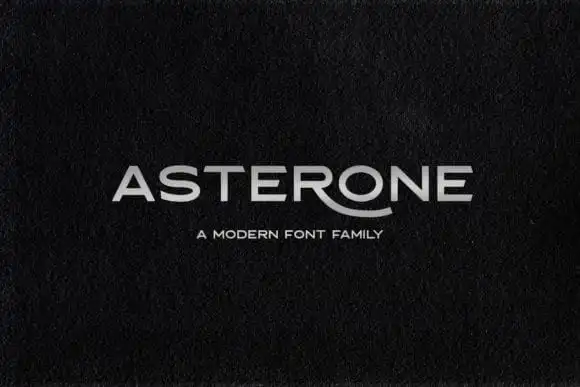
Asterone Sans Serif Font
Asterone Sans Serif é uma escolha perfeita para designers buscando algo moderno e eficaz. Desenvolvida pela equipe do 99designs, esta fonte sans-serif oferece um design sólido que se destaca por sua simplicidade elegante. Seu estilo limpo e minimalista permite criar headlines impactantes com rapidez e facilidade. Para tornar seus logotipos mais únicos, Asterone também traz alternativas estilísticas e ligaturas personalizadas. Esta fonte serve como uma inspiração poderosa para projetos futuristas, proporcionando a você a liberdade de criar designs inovadores apenas com um clique. Com Asterone Sans Serif, é simples transformar suas ideias em realidade, oferecendo um design que combina elegância e eficiência no formato ideal da sans-serif.